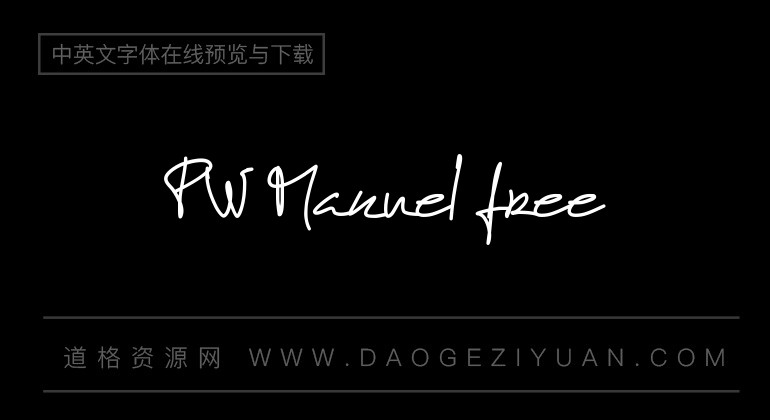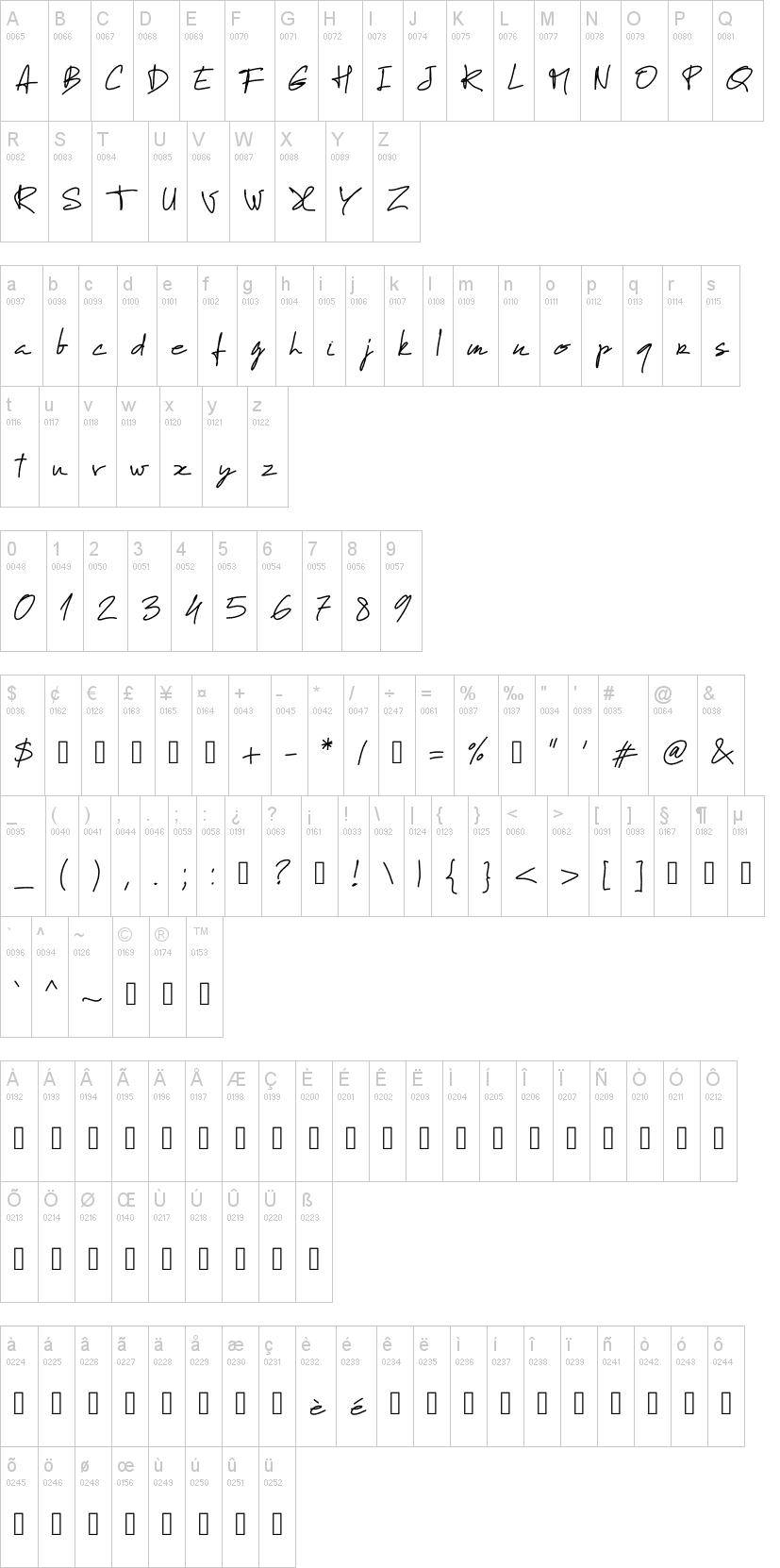
PW Manuel free
PW Manuel Free是一款免费的字体,由Paulo W的设计师Manuel Ramos设计,它是一款经典的英文字体,具有优美的外观和细腻的线条。这款字体有着简洁的外观,可以让文字看起来更加简洁大方,而且还有着深厚的历史背景,可以让文字更加有文化感。它的字体设计非常的精美,可以用于报纸、杂志等印刷品的设计,也可以用于网页设计,让文字更加有个性。
PW Manuel free是一款非常不错的手写艺术字体,具有很好的视觉感,适合于文化类的宣传设计、商业类品牌的广告和产品包装设计以及个性化文字排版等较多场景。
PW Manuel free字符映射图